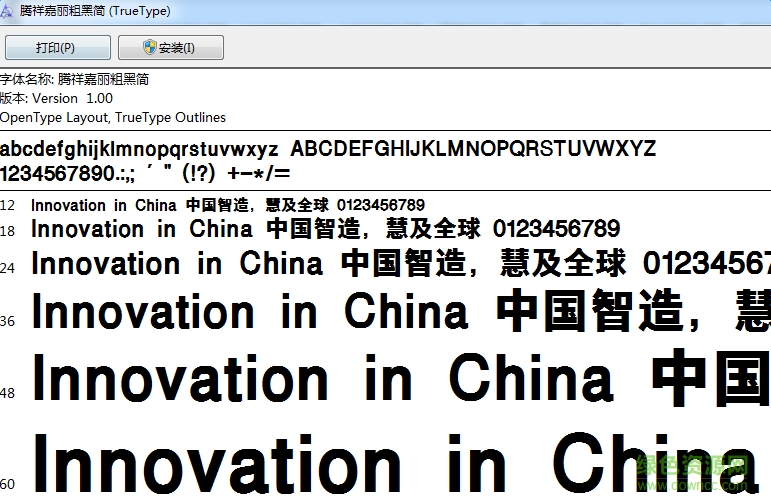
騰祥嘉麗粗黑簡(jiǎn)體
騰祥嘉麗粗黑簡(jiǎn)字體是一款應(yīng)用于設(shè)計(jì)方面的個(gè)性字體,改字體可用于藝術(shù)設(shè)計(jì)、包裝印刷、簽名設(shè)計(jì)、圖形設(shè)計(jì)等領(lǐng)域,有喜歡的朋友可免費(fèi)下載收藏。
騰祥嘉麗粗黑簡(jiǎn)字體是一款極具個(gè)性的字體,改字體形體非常方正,有喜歡的朋友可以來綠色資源網(wǎng)下載體驗(yàn)!